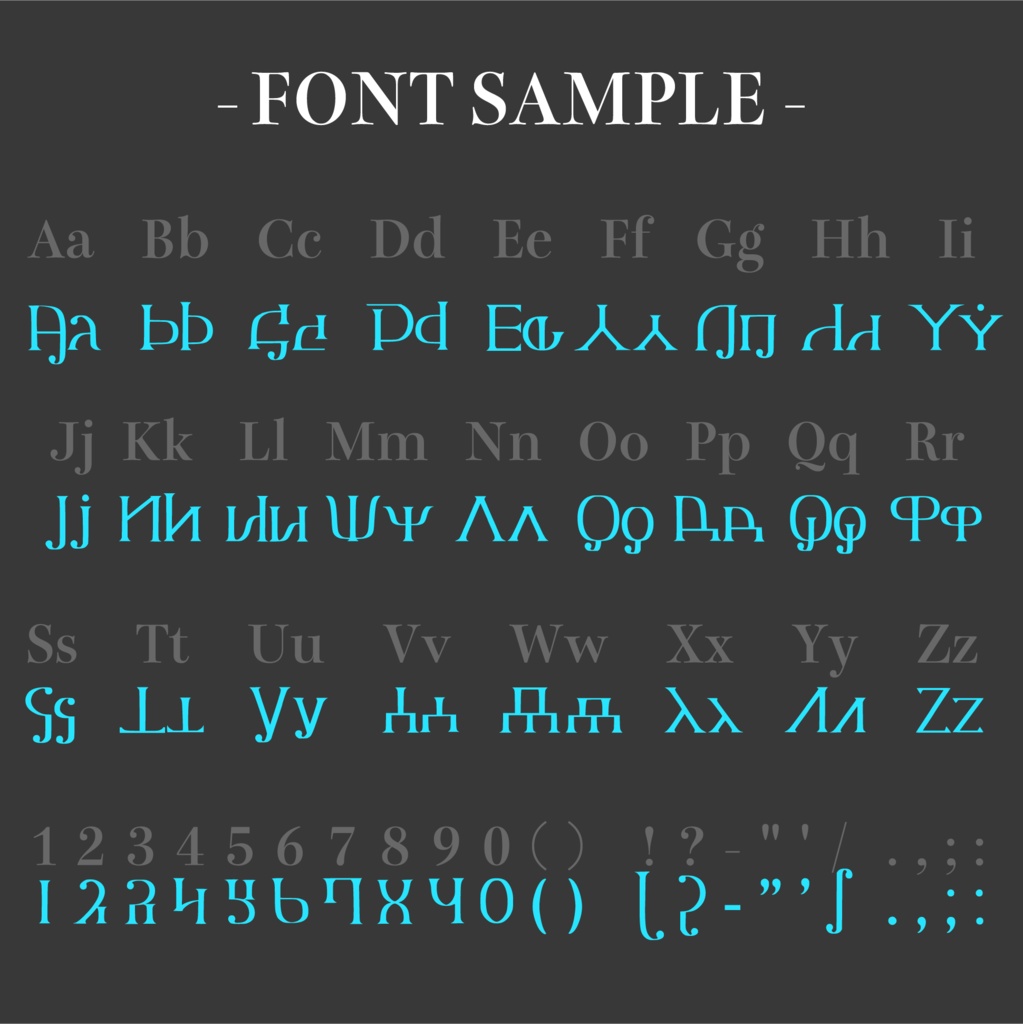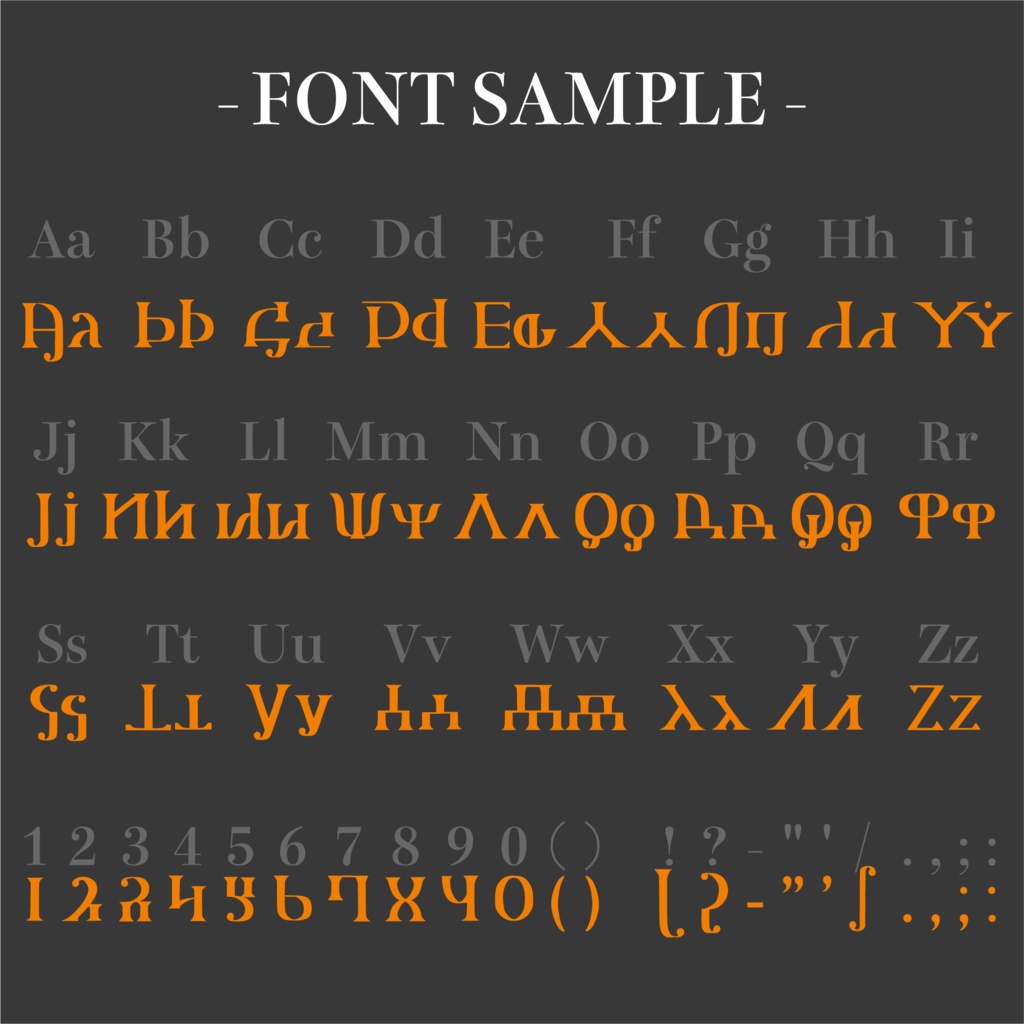
Fantasy Font | Gavelk ファミリー
ファンタジー系のTRPG等で使うことを想定して制作したフォントです。 基本となる共通言語に用いられている文字を意識して制作しました。 セリフ体として「Gavelk Serif」をRegularとBold、手書き書体として「Gavelk Hands」を同梱しています。 ---- 「Fantasy Font シリーズ 全6書体全部入りセット」をご購入すると格安で入手できてお得です。ぜひこちらをどうぞ! https://soya-workshop.booth.pm/items/4766747